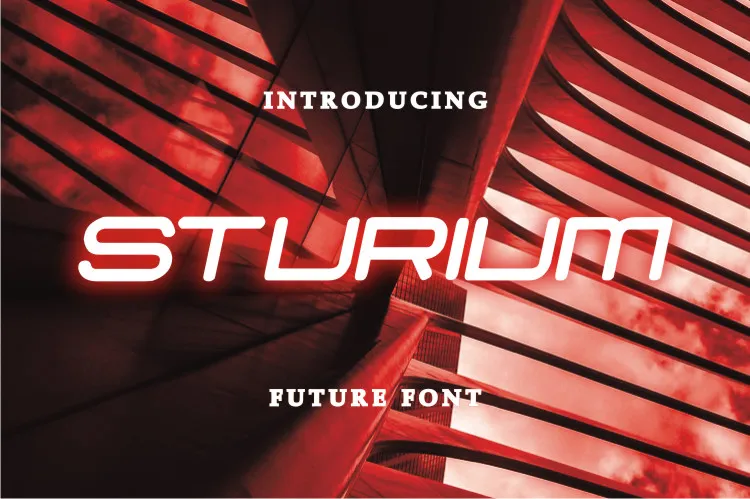
A fonte ‘Sturium Font’ é perfeita para aqueles que buscam uma mistura única entre a tecnologia moderna e a elegância clássica. Esta fonte de estilo display, criada pela Letterfiastudio, oferece um visual cool e futurista, ideal para escritas web, cartões de negócios ou qualquer outra aplicação que requer um toque único. Com uma disposição fluida e detalhes atraentes, a ‘Sturium Font’ tornará seus projetos mais atrativos e memoráveis, sem dúvida deslizando sua atenção para o público-alvo certificado. Não importa se você está criando conteúdo digital ou impresso, esta fonte é capaz de destacar seu trabalho, deixando uma impressão duradoura na mente do consumidor.
Designer: letterfiastudio